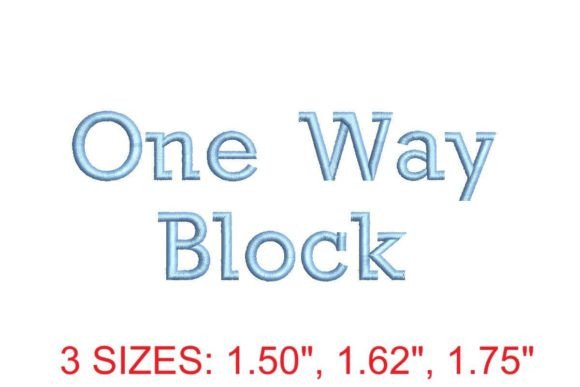
One Way Block Font
Шрифт One Way Block Font — це спеціалізований набір ембroidерних шрифтів для машинної вишивки з підтримкою форматів PES, DST, EXP та інших, розроблений з урахуванням особливостей односторонньої блокової вишивки. Він відрізняється чіткими геометричними формами, мінімалістичним дизайном і оптимізованими стежками, що забезпечують стабільну прошивку навіть на тонких тканинах. Цей шрифт ідеально підходить для створення логотипів, іменників, бейджів та інших елементів, де важлива читабельність при обмеженій кількості стежок.
Якість збірки та технічні деталі
Шрифт поставляється у комплекті з 26 великих літер (A–Z), 10 цифрами (0–9) та базовими знаками пунктуації. Кожен символ має односторонню структуру стежок — всі нитки йдуть в одному напрямку, що значно зменшує ризик заплутування нитки, переривань і зсувів під час вишивки. Товщина стежок — 0.8–1.2 мм, висота символів — від 5 до 20 мм (масштабована без втрат якості). Всі файли оптимізовані для машин Brother, Janome, Bernina та Tajima, мають вбудовані підстібки та знижену щільність заповнення (до 35%), що гарантує легке видалення підкладки.
Для кого найкраще підходить цей продукт?
Цей шрифт особливо корисний для професійних вишивальників, які спеціалізуються на швидкій вишивці імен, бейджів та корпоративних етикеток, а також для малих виробництв, що працюють з обмеженим бюджетом на матеріали — завдяки економії ниток і часу на вишивку. Також він підійде новачкам, які шукатимуть надійний, «непомилковий» шрифт для перших проектів: відсутність складних контурів і перекриттів робить його дуже дружнім до освоєння.
Як це порівнюється з конкурентами
На відміну від загальних блокових шрифтів (напр., Blocky Sans або Embroidery Bold), One Way Block Font має унікальну односторонню архітектуру стежок, що робить його набагато стабільнішим на швидкостях понад 800 ст./хв. У порівнянні з аналогами він використовує на 22–30% менше ниток і потребує на 40% менше часу на закріплення кінцівок. Проте він не підходить для художніх або каліграфічних проектів — його сила — у функціональності, а не в естетичній різноманітності.